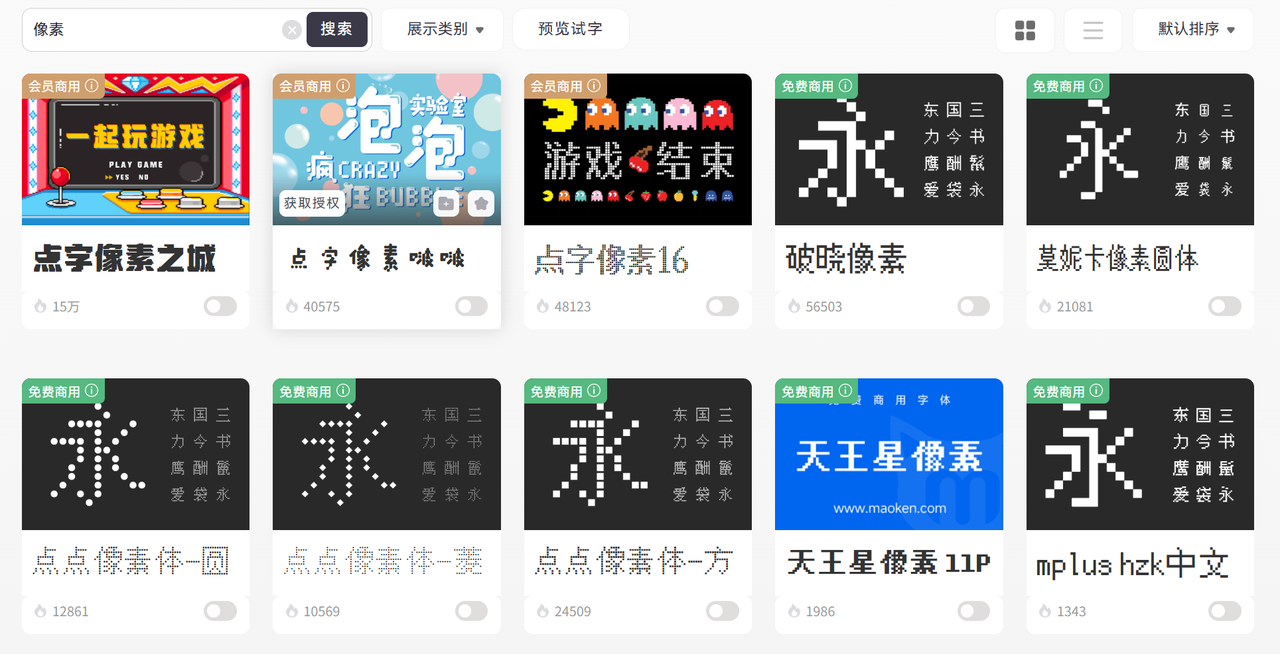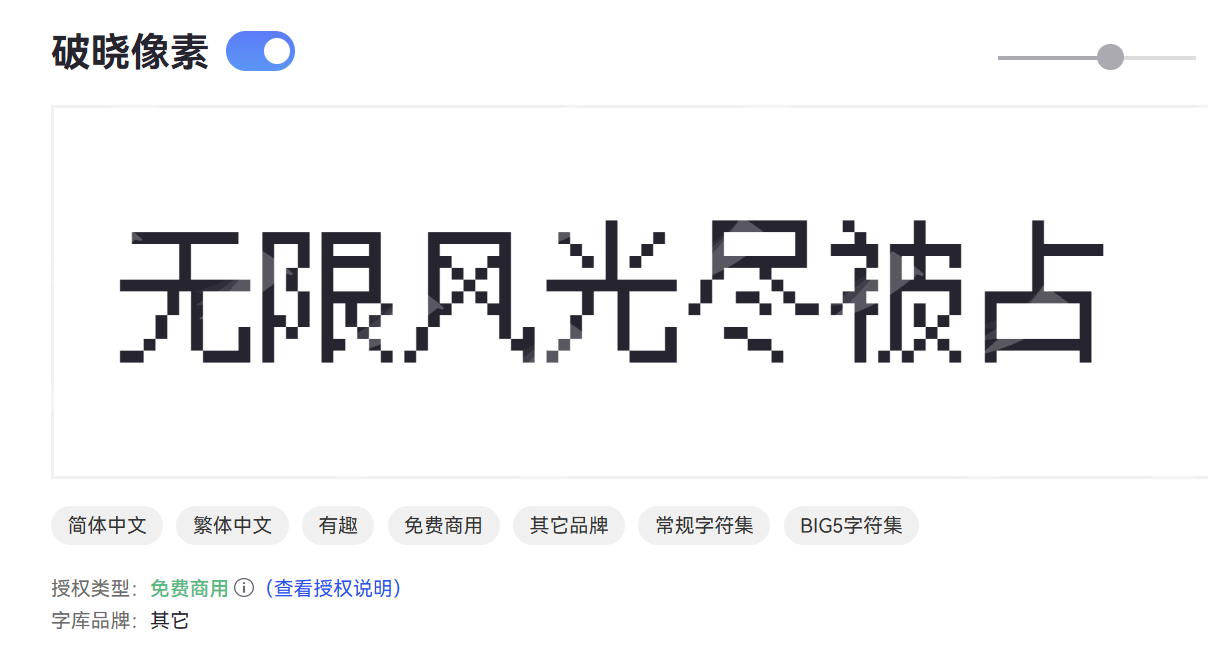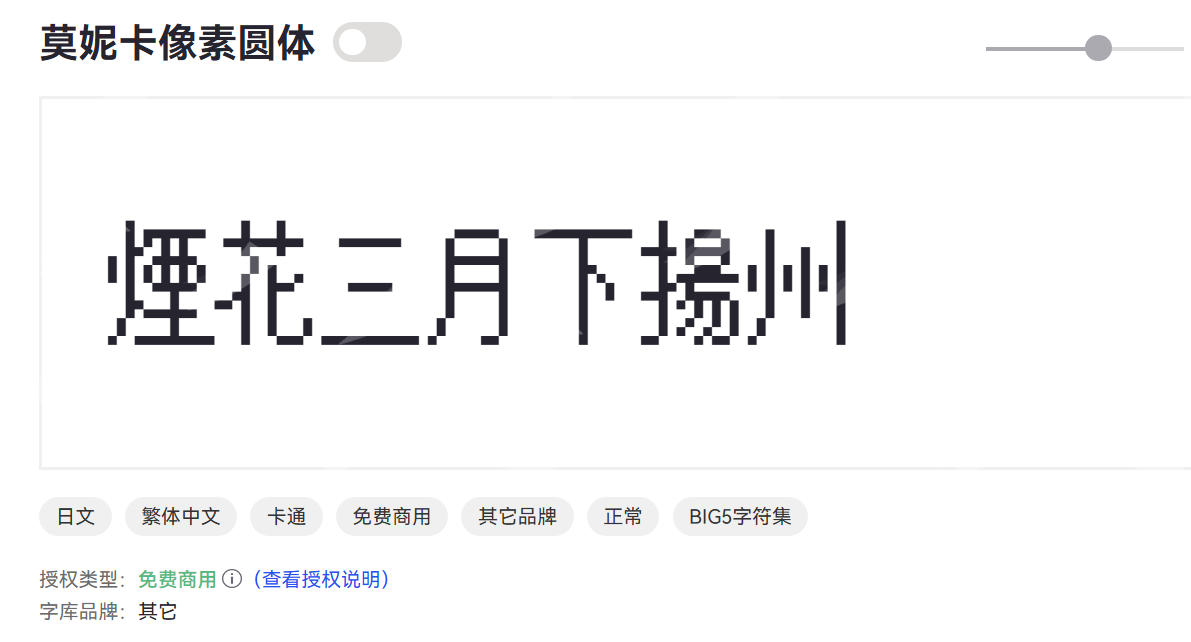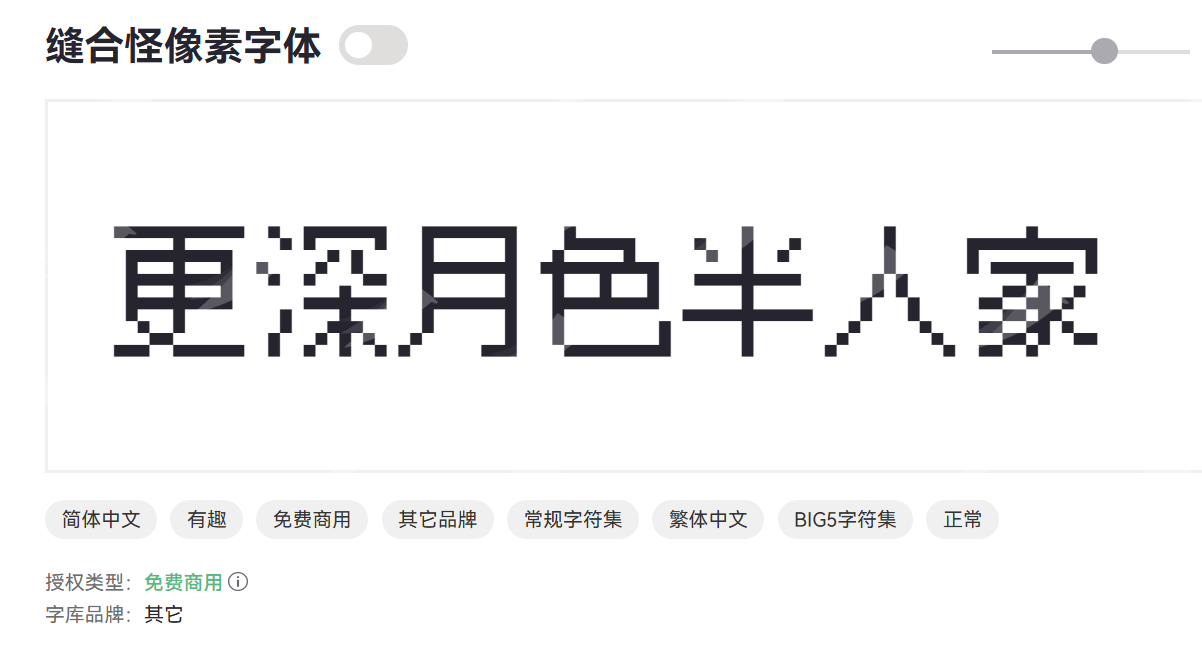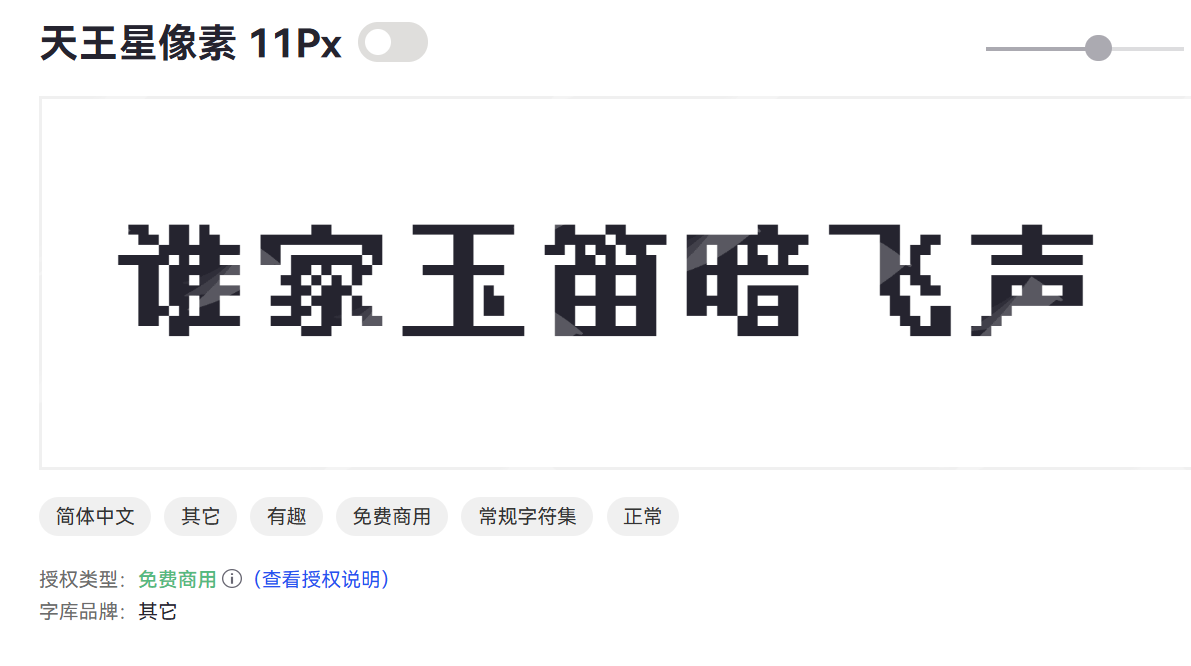
如何下载喷码字体,免费下载喷码字体的6个平台
甲方要求做出那种“刚从生产线打出来”的喷码效果。你兴致勃勃地去搜“喷码字体”,结果发现要么是收费的,要么下载下来只有英文没有中文,或者干脆是乱码。
想要找到适合喷码效果的免费商用字体,只要找对几个靠谱的平台,你就能放心大胆地用在电商海报、产品包装、工业标签上。本文给大家分享 6 个可以下载免费商用喷码字体的平台。
一、在字由里找到的几款喷码风字体
字由是我最常用的字体管理工具之一,它最大的好处是每个字体都标注了版权状态,特别是它的“免费商用”专区,让我能快速找到合适的喷码字体,字由提供分类筛选和搜索功能,但是直接搜索“喷码”,估计很难找到。
可以尝试搜索“像素”
破晓像素
破晓像素是一款非常经典的开源像素字体,以极高的清晰度著称。字形工整,在极小的尺寸下(如 12px)依然能保持非常好的可读性。
莫妮卡像素圆体
莫妮卡像素圆体在像素字体的基础上增加了“圆角”的处理,相比传统像素字体的硬朗,莫妮卡像素圆体看起来更加可爱、柔和、有温度。适合可爱风格的游戏(如经营模拟类)、手办展示牌、社交媒体的像素风海报设计。
合怪像素字体
合怪像素字体是一款由开发者(如 TakWolf 等)通过脚本“缝合”了多个开源字库而成的字体。这款字体通过整合不同字体的字形,确保了在游戏或应用中极少出现“缺字”(即方块乱码)的情况。
天王星像素
天王星像素具有独特的设计感,线条可能比标准的像素字体更具表现力。这种字体通常用于游戏标题、UI 装饰或需要特定视觉个性的场合。
二、还有哪些平台可以获取免费商用喷码字体?
除了字由,我还收藏了以下5个平台。它们各有特色,能帮你找到更多不同风格的喷码字体。
站酷
站酷不仅是设计社区,更是一个免费商用字体的大本营。很多国内知名设计师会在这里发布开源字体,比如“站酷文艺体”“站酷快乐体”等。虽然它们不是专门的喷码字体,但你可以通过调整字间距和添加效果来模拟。站酷的字体版权声明通常很清晰,只要认准“免费商用”标签,就可以放心用。我经常在这里淘一些风格独特的字体,用在创意包装上。
字体天下
这是一个老牌字体下载站,分类非常细致。你可以直接搜索“点阵”“像素”“工业”等关键词,找到很多接近喷码效果的字体。不过要注意,这里既有免费也有付费字体,下载前一定要看清页面上标注的“免费商用”字样。我的习惯是只看那些明确标注了“免费可商用”的字体,并且会截图保存授权信息。
免费字体网
这个网站界面很简洁,没有太多广告,收集了大量开源字体。它的优势在于下载通道很顺畅,不需要注册登录。虽然字体数量不如大站多,但每款都经过筛选,基本都能商用。我有时会在这里找一些冷门的点阵字体,用在特殊项目上。
字体家
这是一款类似字由的字体管理软件,也有网页版。它的免费商用专区同样很实用,而且社区活跃度高,经常能看到设计师分享排版技巧。你可以通过它的智能匹配功能,上传一张带有喷码效果的设计图,它会推荐相似的免费字体。这个功能对我这种懒人来说很友好。
GitHub
如果你不介意稍微折腾一下,GitHub是获取最纯净字体源文件的好地方。很多独立开发者会把字体项目托管在这里,并采用MIT、Apache等宽松的开源协议。搜索“Chinese font”并筛选“License”为“MIT”的项目,你就能找到一些很有特色的点阵字体。下载后可能需要手动安装,但胜在完全免费、无任何后顾之忧。
三、一些实用的小技巧
光下载字体还不够,想让喷码效果更真实,我通常会做这几步:
1. 调整字间距:喷码机的字符间距通常比较均匀,所以我会把字间距调小一点,甚至设置为负值,让字符看起来更紧凑。
2. 添加杂色:用Photoshop或Illustrator给文字图层叠加一点“添加杂色”滤镜,模拟喷墨的颗粒感。
3. 降低透明度:把文字透明度降到80%左右,再复制一层稍微偏移,制造轻微的重影,看起来就像刚喷上去的。